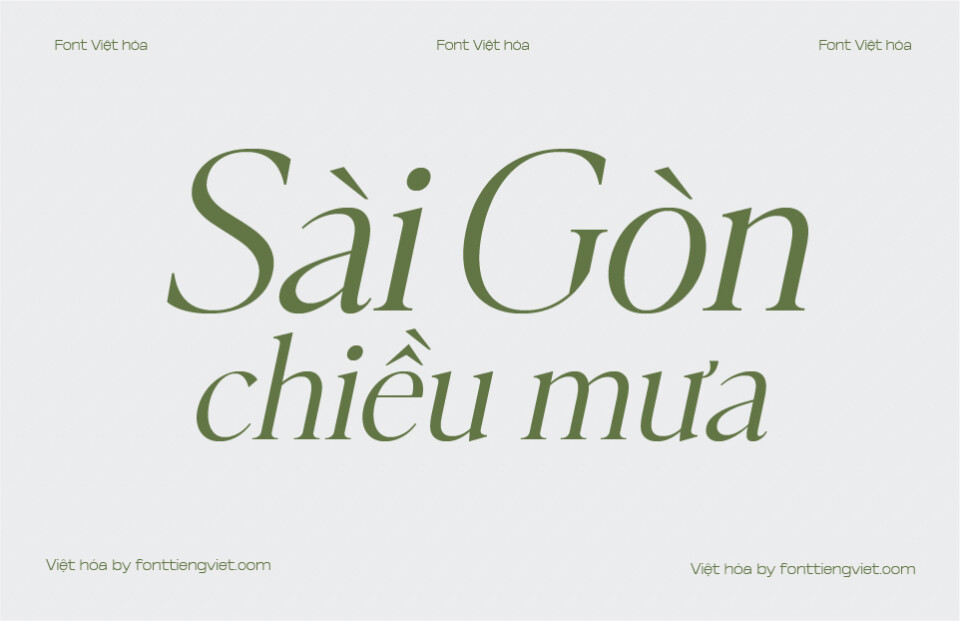
Font Việt hóa 1FTV VIP British Green Italic
Font Việt hóa 1FTV VIP British Green Italic – Đẳng cấp nghệ thuật chữ viết nghiêng tinh tế
Giới thiệu về Font Việt hóa 1FTV VIP British Green Italic
Trong thế giới thiết kế đồ họa hiện đại, việc lựa chọn một bộ Font Miễn Phí chất lượng không chỉ giúp truyền tải nội dung mà còn thể hiện cá tính riêng biệt của tác giả. Font Việt hóa 1FTV VIP British Green Italic là một trong những bộ font chữ tiêu biểu, mang phong cách cổ điển của Anh Quốc kết hợp với nét hiện đại, thanh thoát. Đây là phiên bản nghiêng (Italic) đầy ấn tượng, giúp tạo điểm nhấn mạnh mẽ cho các tác phẩm sáng tạo từ biểu trưng đến thiệp mời sang trọng.
Đặc điểm thiết kế của Font Việt hóa 1FTV VIP British Green Italic
Bộ font này được trau chuốt tỉ mỉ với những đường nét uốn lượn mượt mà, tạo cảm giác chuyển động linh hoạt nhưng vẫn giữ được sự vững chãi. Điểm đặc biệt của Font Việt hóa 1FTV VIP British Green Italic chính là sự cân bằng giữa độ dày và độ mảnh, tạo nên một tổng thể hài hòa về mặt thị giác. Khi áp dụng vào các tiêu đề chính hoặc các đoạn trích dẫn quan trọng, kiểu chữ này giúp người xem cảm nhận được sự chuyên nghiệp và đẳng cấp nghệ thuật cao.
Tại sao nên sử dụng Font Việt hóa 1FTV VIP British Green Italic?
Việc sở hữu Font Việt hóa 1FTV VIP British Green Italic mang lại nhiều lợi thế cho các nhà thiết kế Việt Nam. Trước hết, bộ font đã được tối ưu hóa hoàn toàn hệ thống dấu tiếng Việt, loại bỏ tình trạng lỗi hiển thị khó chịu thường gặp ở các font nước ngoài. Điều này giúp quá trình soạn thảo văn bản trở nên thuận lợi và đồng nhất hơn bao giờ hết.
Ứng dụng trong các lĩnh vực thiết kế
Với vẻ ngoài sang trọng, Font Việt hóa 1FTV VIP British Green Italic cực kỳ phù hợp cho các dự án liên quan đến thời trang, nước hoa, trang sức hoặc các bìa tạp chí nghệ thuật. Ngoài ra, trong môi trường giáo dục, các bạn học sinh và giáo viên có thể sử dụng font chữ này để trang trí báo tường, thiết kế chứng chỉ khen thưởng hoặc làm nổi bật các bài thuyết trình Powerpoint để tạo sự cuốn hút đối với người xem.
Lưu ý khi tùy chỉnh thông số chữ
Khi sử dụng Font Việt hóa 1FTV VIP British Green Italic, hãy chú ý đến khoảng cách giữa các chữ cái (kerning). Do đặc thù là kiểu chữ nghiêng nghệ thuật, việc điều chỉnh khoảng cách hợp lý sẽ giúp văn bản trông thoáng đãng và dễ đọc hơn, đặc biệt là khi in ấn trên các chất liệu giấy mỹ thuật cao cấp.
Kết luận về bộ Font Việt hóa 1FTV VIP British Green Italic